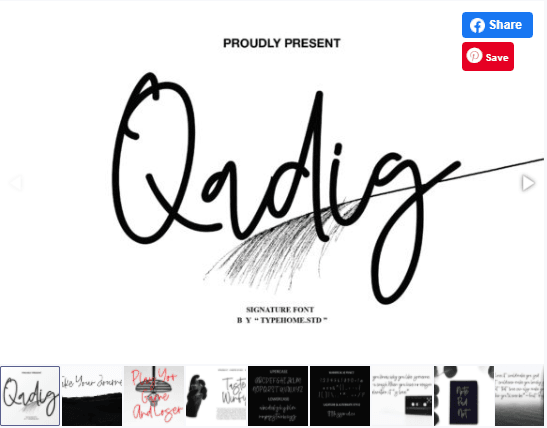
Qadig Font
Qadig - это тонкий буквенный, мягкий и нежный рукописный шрифт. Он прекрасно смотрится на различных дизайнах, требующих индивидуального стиля, таких как приглашения на свадьбу, открытки с благодарностью, свадьбы, поздравительные открытки, логотипы и так далее.